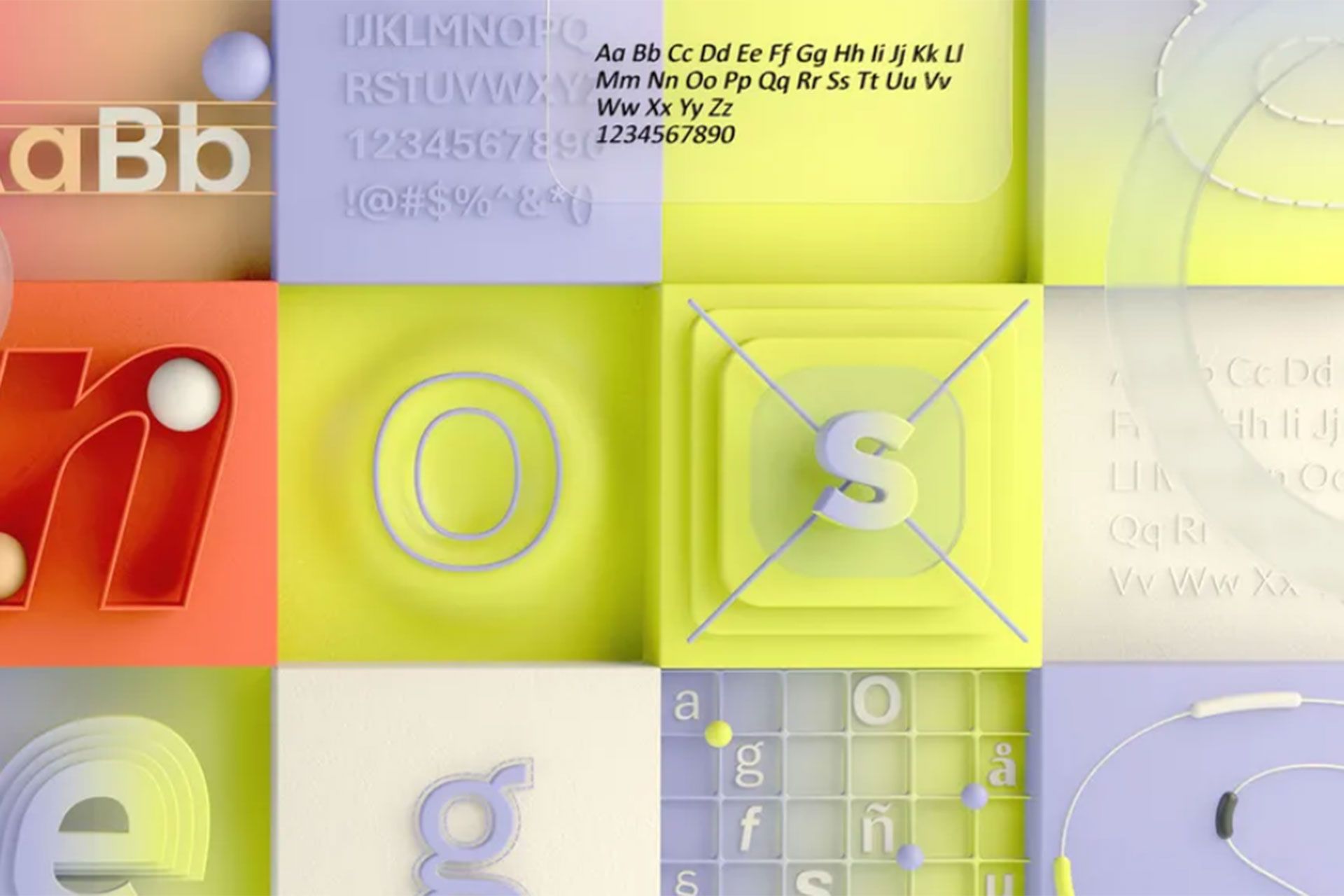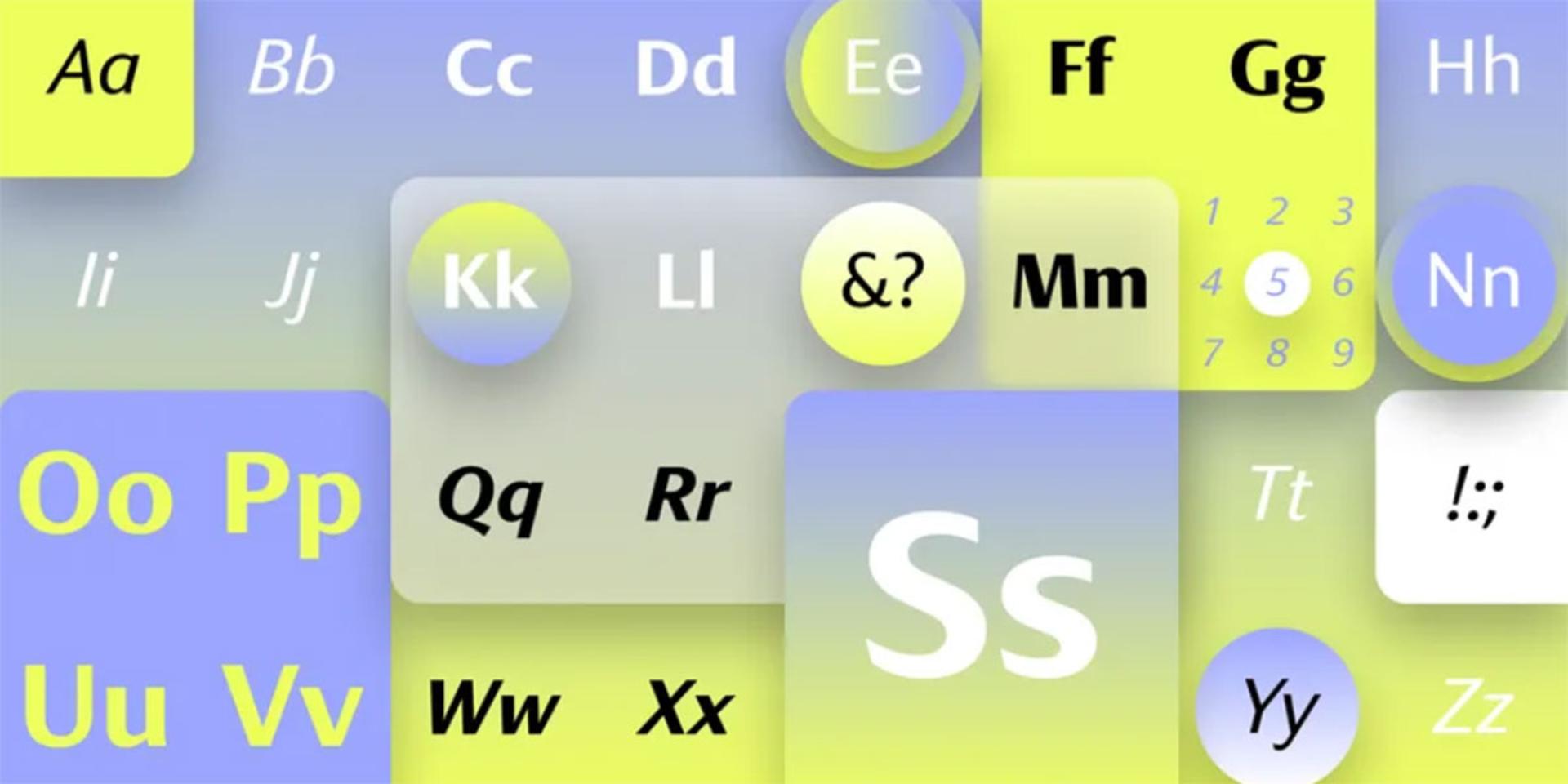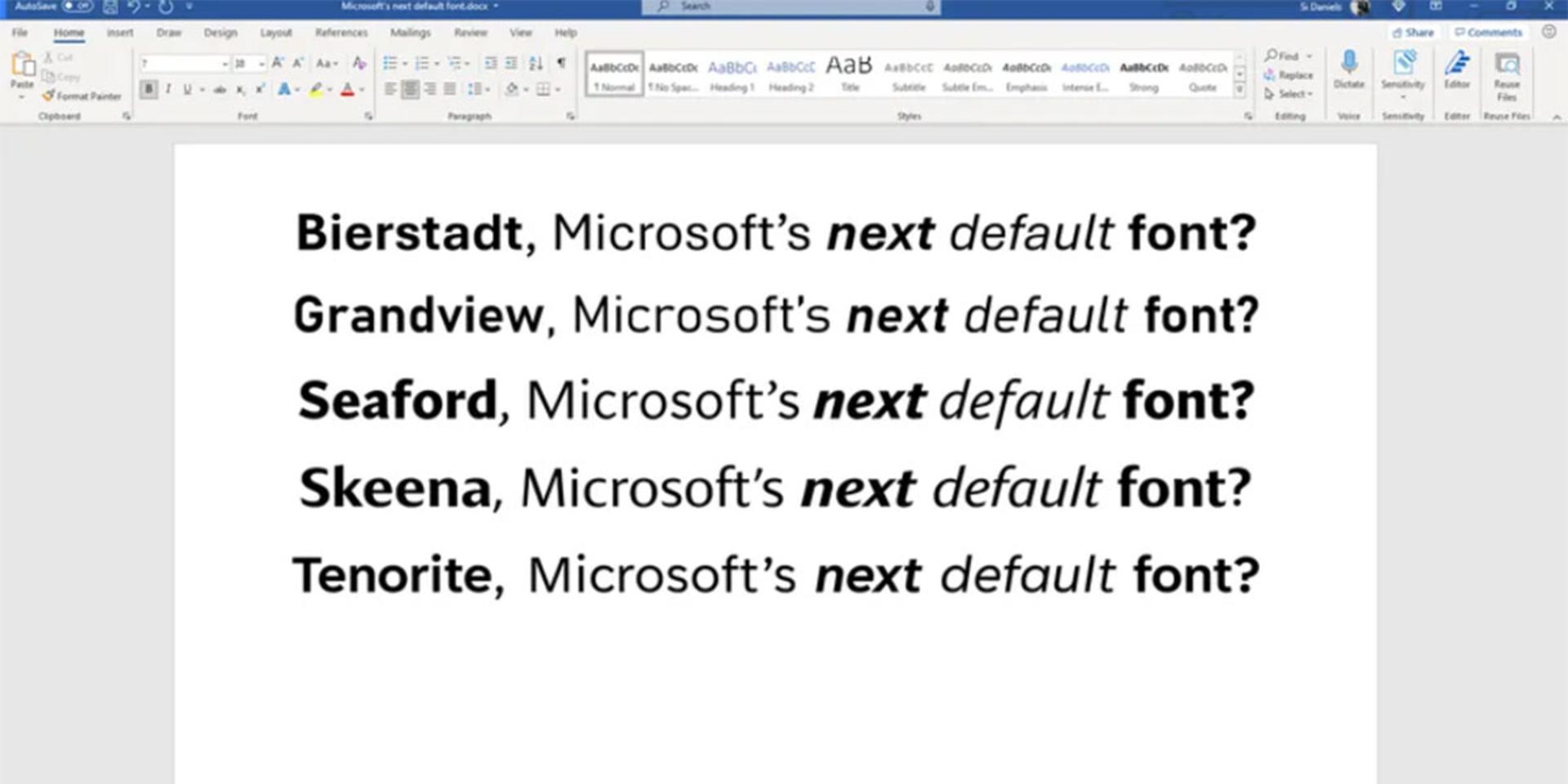
مایکروسافت برای تغییر فونت پیشفرض مایکروسافت آفیس از کاربران این مجموعه نرمافزار درخواست همفکری کرده است و میخواهد از بین ۵ گزینه مورد نظر، یکی را انتخاب کنند.
به گزارش The Verge، مایکروسافت قصد دارد سال میلادی آینده فونت پیشفرض آفیس را تغییر بدهد و از همه میخواهد در انتخاب کردن گزینهی بعدی به آن کمک کنند. درحالیکه بیش از ۵۰۰ فونت مختلف در ورد وجود دارد، مایکروسافت، پنج فونت جدید برای مجموعهی آفیس در نظر گرفته است. در واقع این کار به منظور فاصله گرفتن از فونت Calibri انجام شده است که نزدیک به ۱۵ سال بهعنوان گزینه پیشفرض آفیس استفاده میشود.
پنج فونت جدید sans-serif دارای سبکهای مختلفی از جمله سنتی و مدرن هستند و حتی یکی از آنها با الهام از علائم جاده و راهآهن آلمان طراحی شده است. مایکروسافت از امروز شروع به جمعآوری بازخورد درباره این پنج فونت جدید کرده و قصد دارد یکی را بهعنوان فونت جدید پیشفرض آفیس در سال ۲۰۲۲ تنظیم کند. در ادامه میتوانید این فونتهای جدید را مشاهده کنید.
مورد اول یعنی Tenorite توسط ارین مک لاولین و وی هوانگ طراحی شده است و سبکی سنتیتر از باقی گزینهها دارد. فونت مذکور بهنوعی نسخهی مدرنتر Times New Roman است که از چند دهه پیش در آفیس مورد استفاده قرار گرفته؛ اما دارای کاراکترهای بزرگتر و علائم نگارشی واضحتر است.
به نظر میرسد Skeena، ساختهشده توسط جان هادسون و پاول هانسلو، از طراحی فونتهایی متعلق به بازههای زمانی مختلف الهام گرفته شده است. فونت مذکور دارای تغییرات زیادی در قسمتهای ضخیم و نازک حروف است و منحنیهای بسیار مشخصی روی حروفی مانند S،اA و J دارد.
بهعنوان گزینه سوم Bierstadt را در اختیار داریم که استیو ماتسون از تایپوگرافی سوئیسی در اواسط قرن ۲۰ برای طراحی آن الهام گرفته است. پایان حروف بهطور واضحی قطع شدهاند؛ اما برای جلوگیری از مشاهده مشکلات معمول در فونتهای اینچنینی، کمی در طراحی کاراکترها دقت بیشتری شده است. Helvetica مشهورترین نمونه این نوع فونت grotesque san serif است. طراح آن سعی کرده در اثر خود تضادهایی با فونت Arial داشته باشد. ماتیسون این فونت را از روی اسم صخرهای در کلرادو نامگذاری کرده است که او را به یاد کوههای آلپ سوئیس میاندازد.
سپس فونت Seaford را مشاهده میکنیم که توسط توبیاس فریر-جونز، نینا استوسینگر و فرد شالکراس طراحی شده است و از آنجایی که به سبک قدیمی متن کلاسیک serif شباهت دارد، بیشتر از بقیه گزینهها برای ما آشنا است. گفته میشود طراحان برای یافتن راهی عملی برای بازگرداندن این فونت کلاسیک و ارزشمند، از صندلیهای قدیمی الهام گرفتهاند. پس از بررسی تمام فونتهای جدید مشخص شده که این گزینه از باقی موارد برای خواندن اسناد طولانی مناسبتر است.
در نهایت به Grandview میرسیم که جالبتر از همه موارد دیگر است. طراح این فونت که از علائم کلاسیک جاده و راهآهن آلمان الهام گرفته شده، فردی به نام آرون بل است. درست مانند علائم جادهای، این فونت بهگونهای طراحی شده که بهراحتی قابل خواندن باشد؛ تنها تغییراتی در آن صورت گرفته است تا باعث راحتی خواندن متنهای بلند شود. بر اساس روحیه استاندارد صنعتی آلمان، به نظر میرسد Grandview بهویژه در اسلایدهای پاورپوینت کارایی بسیار خوبی داشته باشد.